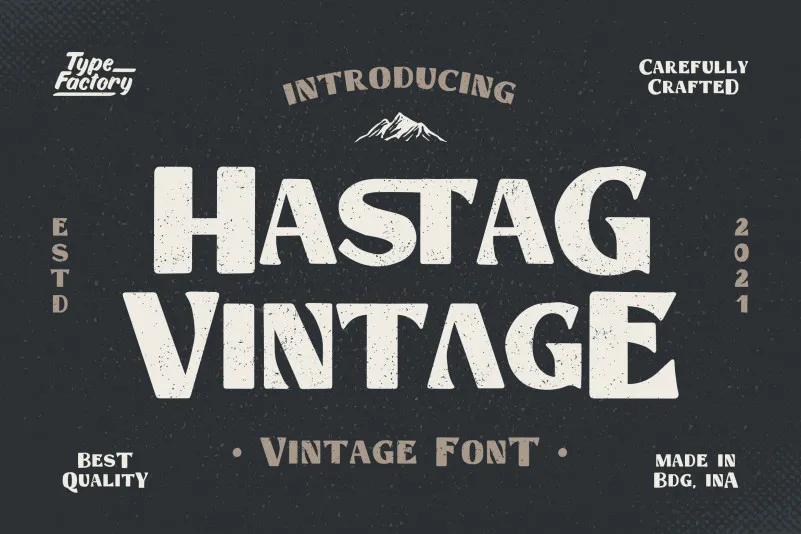
A Hastag é uma fonte de tipo sans-serif vintage criada pelo Typefactory, que incorpora elementos de estilo antigo. Suas linhas clean e modernas se combinam com detalhes que remetem ao passado, proporcionando um equilíbrio entre a elegância do design clássico e a funcionalidade da fonte atual. Esta fonte vem com uma ampla variedade de opções, incluindo maiúsculas e minúsculas maiúsculas, números, símbolos, pontuações alternativas, ligaduras e suporte multilíngue. Perfeita para logotipos, cartões de correspondências, faixas, roupas, etiquetas e muitos outros designs. O Hastag é uma escolha ideal para quem busca uma fonte moderna com um toque nostálgico que se adapta a diversos tipos de criação gráfica.